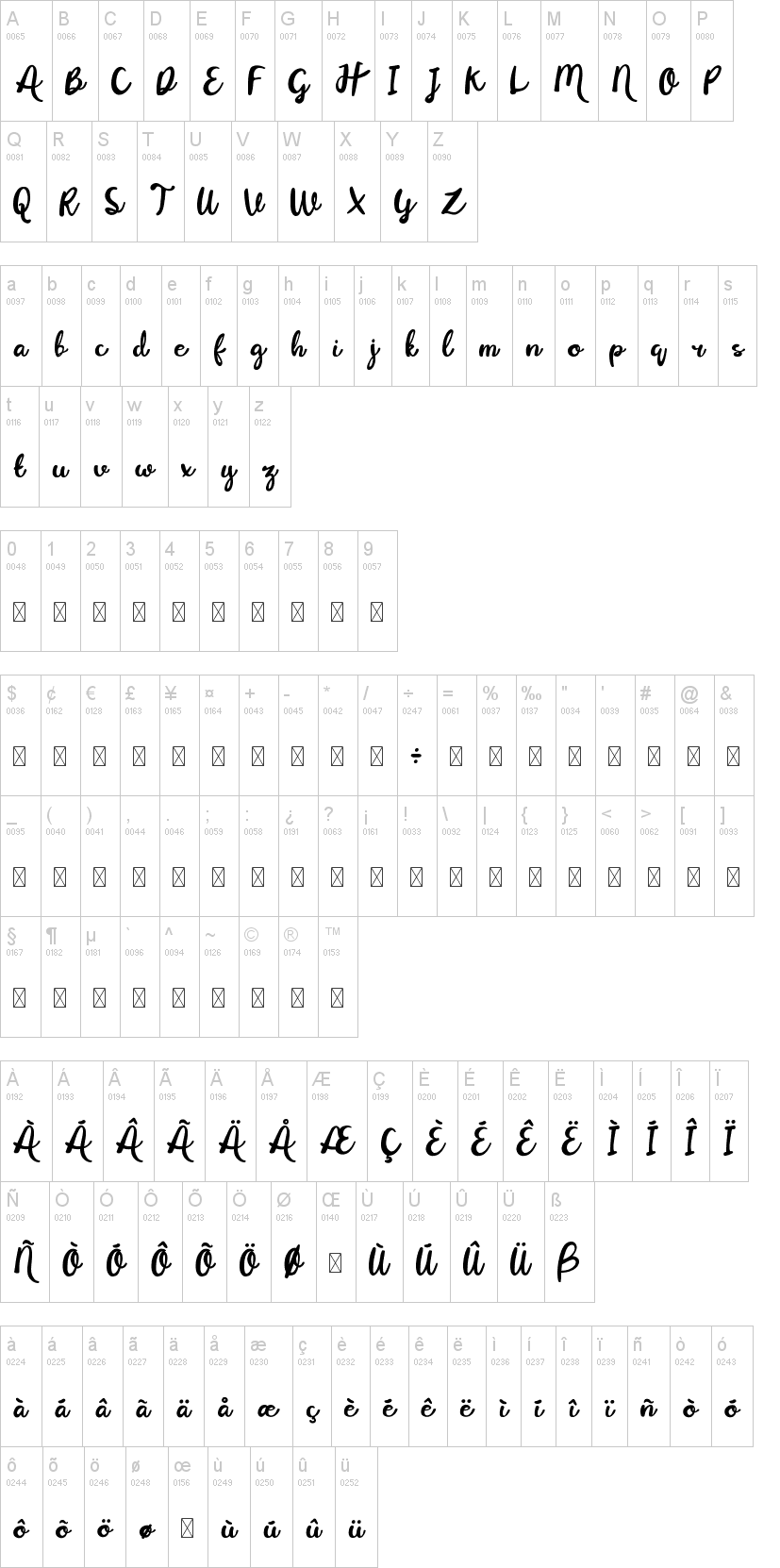
Mimitee
Mimitee 字体是一款简洁时尚的英文字体,它具有细腻的线条和较大的字母间距,适合用于各种宣传海报、标识设计等。它的特点是结构简单,字母间距较大,给人一种轻松、活泼的感觉。Mimitee 字体可以用于网站设计、广告设计、标识设计等,可以提高设计作品的质量。
Mimitee是一款非常不错的手写艺术字体,具有很好的视觉感,适合于文化类的宣传设计、商业类品牌的广告和产品包装设计以及个性化文字排版等较多场景。
Mimitee字符映射图